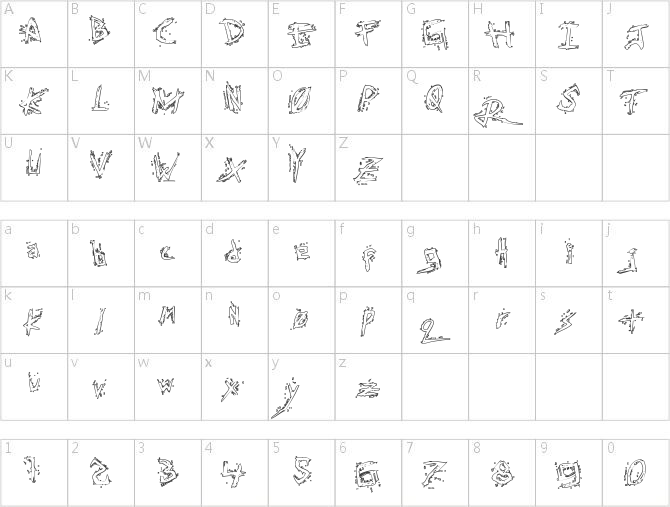
Assassin Nation Outline 詳情頁
Assassin Nation Outline字體字庫是一款讓人賞心悅目、百看不厭的英文字體,適合各類廣告和產(chǎn)品包裝設(shè)計應(yīng)用,字體大小0.35MB,格式為ttf字體,上傳用戶是welking,作者/版權(quán)方為未知